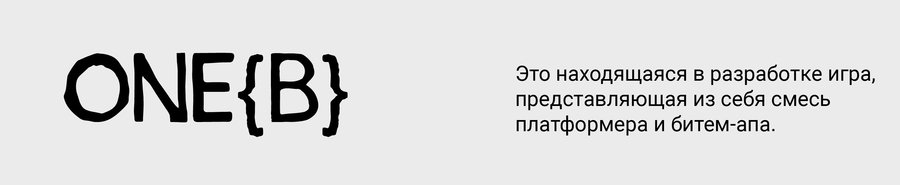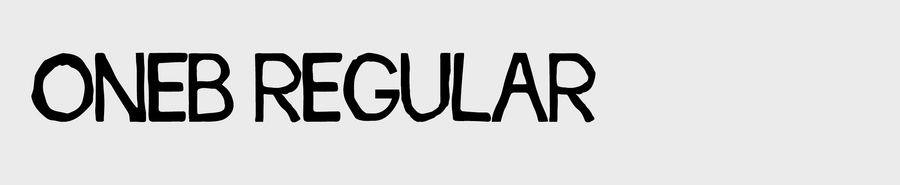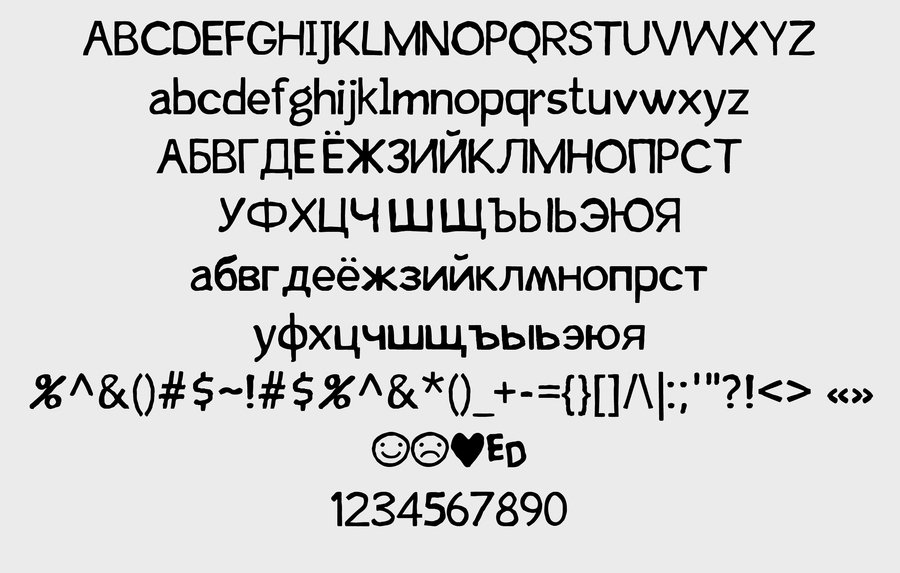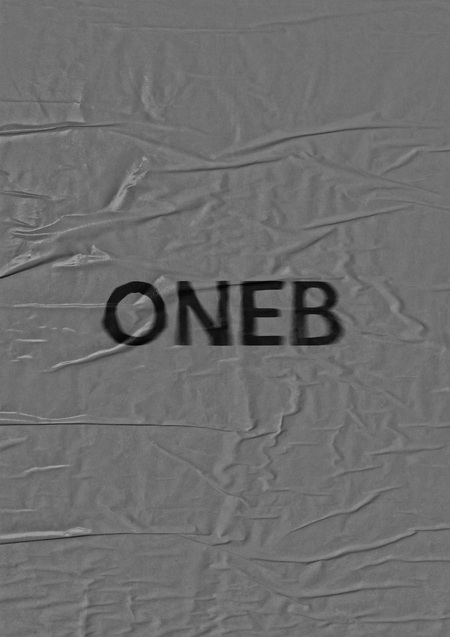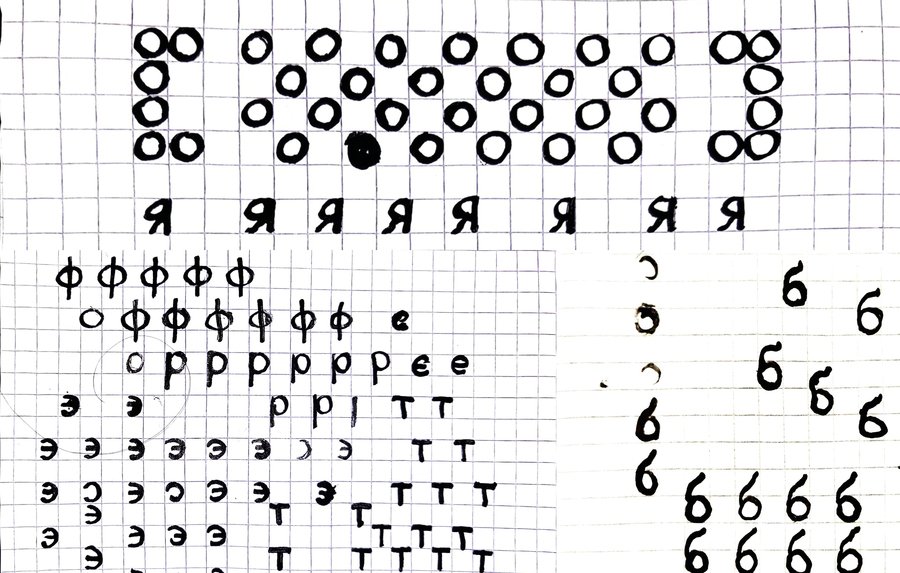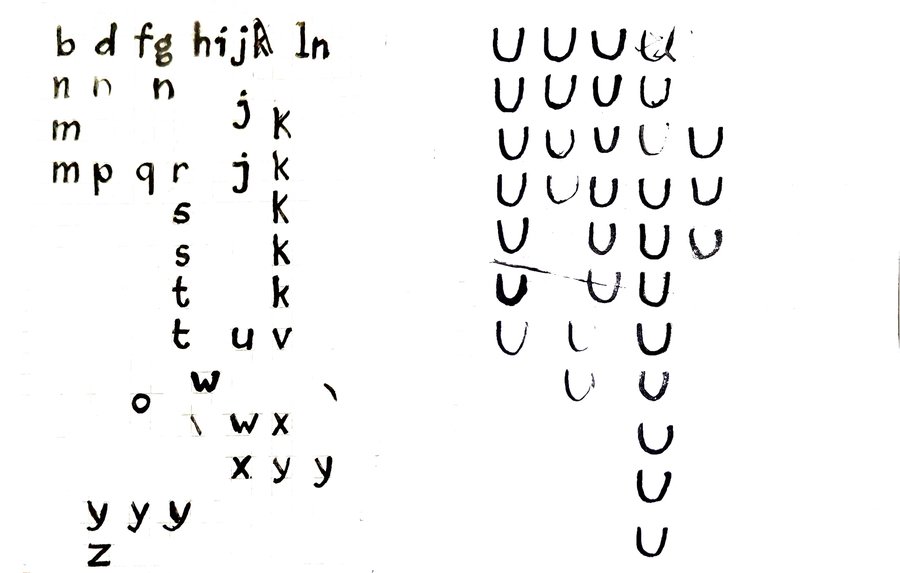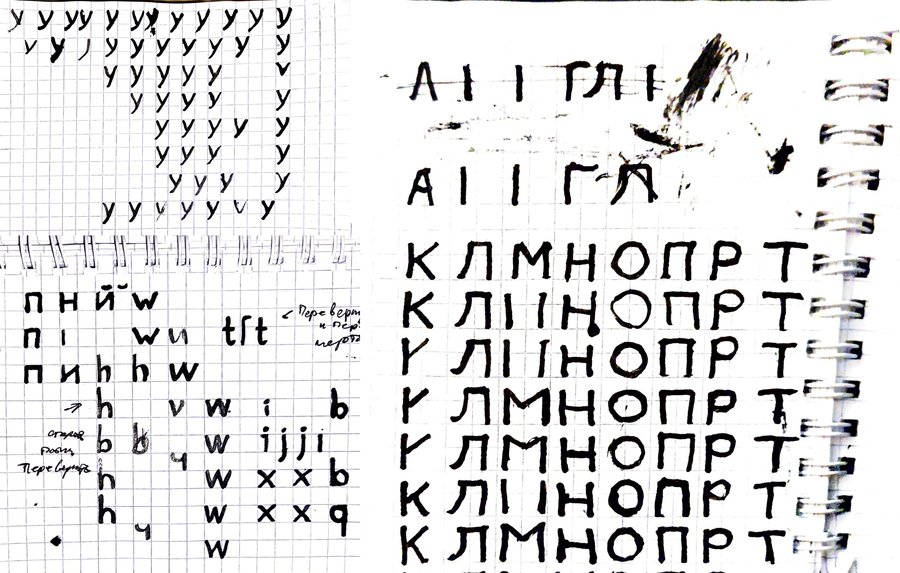
ЗАДАЧА
Шрифт должен передавать будущую хаотичность игрового процесса и вселенной «Онеба».
РИСУНОК ШРИФТА
Во время разработки шрифта в качестве референсов брались граффити с превалирующими квадратными формами в буквах.
Позже с помощью пера и чернил я повторял формы и делал еще эскизы.
Шрифтовая касса ONEB REGULAR
Особые символы
Кассовый набор ONEB THIN
Кассовый набор ONEB PIXEL
НОСИТЕЛИ